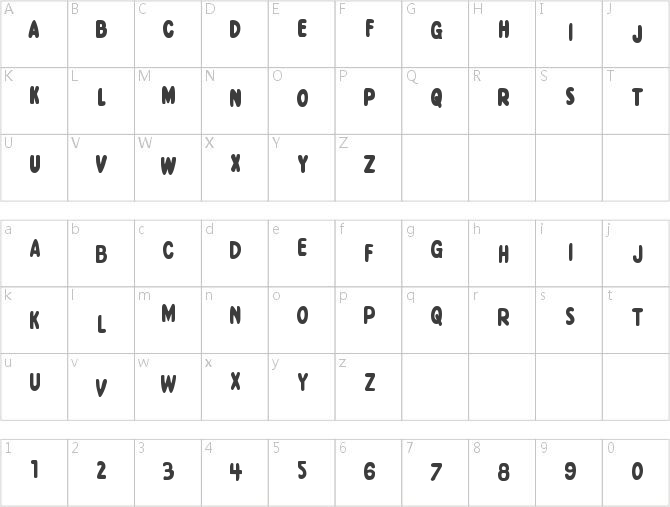
Excelsior-Comics-Regular 詳情頁(yè)
Excelsior-Comics-Regular字體字庫(kù)是一款讓人賞心悅目、百看不厭的英文字體,適合各類廣告和產(chǎn)品包裝設(shè)計(jì)應(yīng)用,字體大小0.04MB,格式為ttf字體,上傳用戶是多拉MO,作者/版權(quán)方為未知